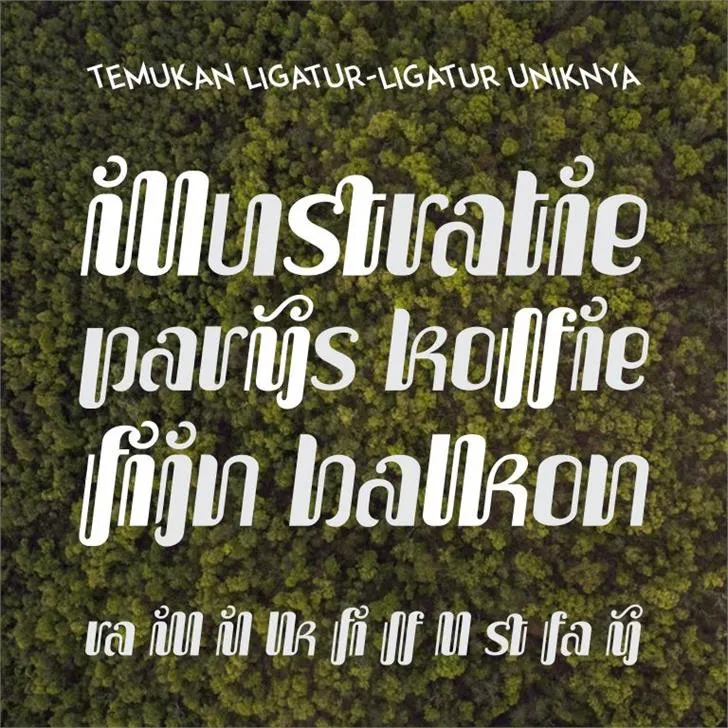
Upakarti font – Download Grátis
A Upakarti é uma elegante fonte pixel art criada por Gunarta Gratis no ano de 2015 para os amantes do design gráfico que curtem a cultura indonesia. Esta fonte traz um toque vibrante e único aos projetos digitais, ideal para aplicativos mobile, logotipos, ilustrações ou qualquer projeto onde você busca uma personalidade única e icônica. Com características modernas e clássicas do design pixel art, Upakarti oferece um contraste atraente que combina perfeitamente com o estilo minimalista dos pixel fonts. Seja em uma aplicação de celular rápida ou em uma imagem ilustrativa elaborada, essa fonte adicionará um toque distintivo e atemporal ao seu design. Para designers brasileiros, especialmente os apaixonados pela cultura local, a Upakarti é uma escolha perfeita para criar projetos que expressam sua identidade. Esse pixel art indiano não apenas traz elementos únicos à sua criação, mas também contribui com um toque de diversão e arte no mundo digital atual. Agora, em sua categoria Pixel Fonts, Hamilton oferece essa fonte para todos nós, permitindo que criamos projetos ainda mais vibrantes. Não importa qual projeto você está trabalhando; a Upakarti é uma escolha sólida para adicionar um toque de personalidade e estilo à sua arte digital.